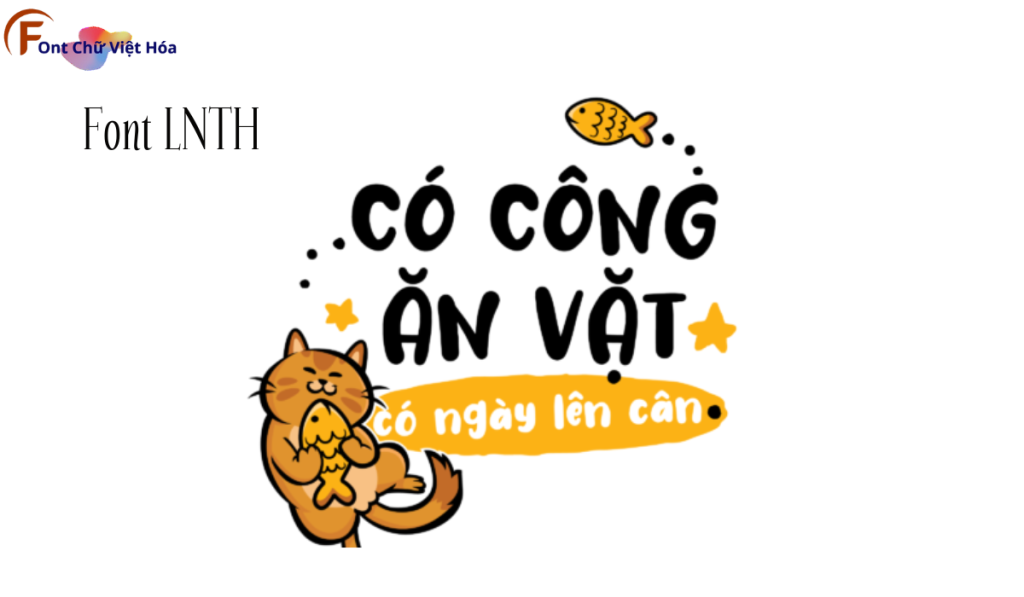
Font LNTH Wash Your Hand Việt Hóa
Font LNTH Wash Your Hand Việt Hóa là một font chữ viết tay, thuộc bộ LNTH, với thiết kế vui nhộn và thân thiện. Phong cách của font này phù hợp với các dự án cần sự gần gũi và ấm áp, như thiệp mời, bìa sách, hoặc bảng hiệu. Font LNTH Wash Your Hand Việt Hóa mang đến sự vui nhộn và dễ nhận diện, ứng dụng trong các lĩnh vực sáng tạo. Đặc điểm hình dạng của font bao gồm các nét bút lông mềm mại và tự nhiên, giúp tăng tính thẩm mỹ và sự chú ý. Việc Việt hóa font giúp người dùng dễ dàng sử dụng trong các thiết kế tiếng Việt, mang lại sự tiện lợi và linh hoạt.